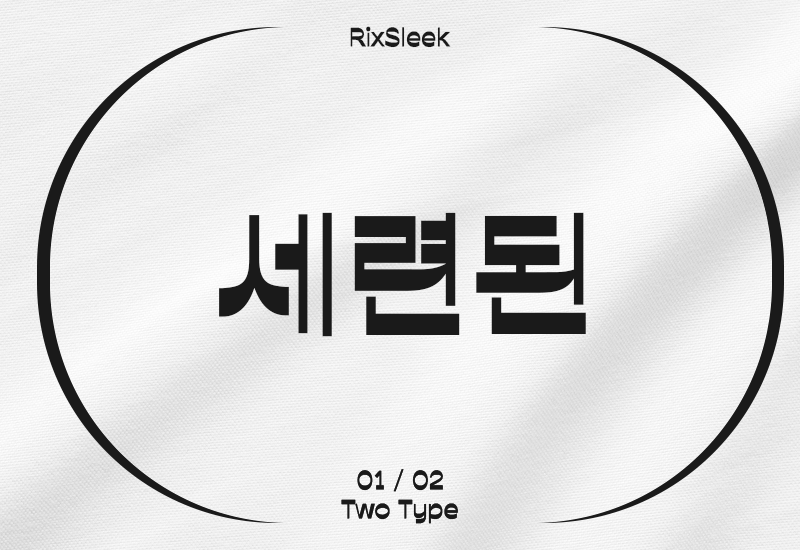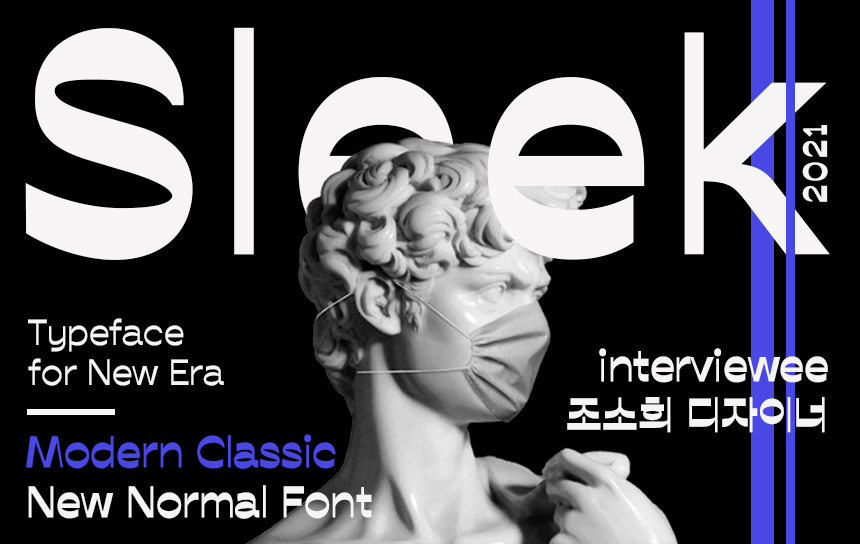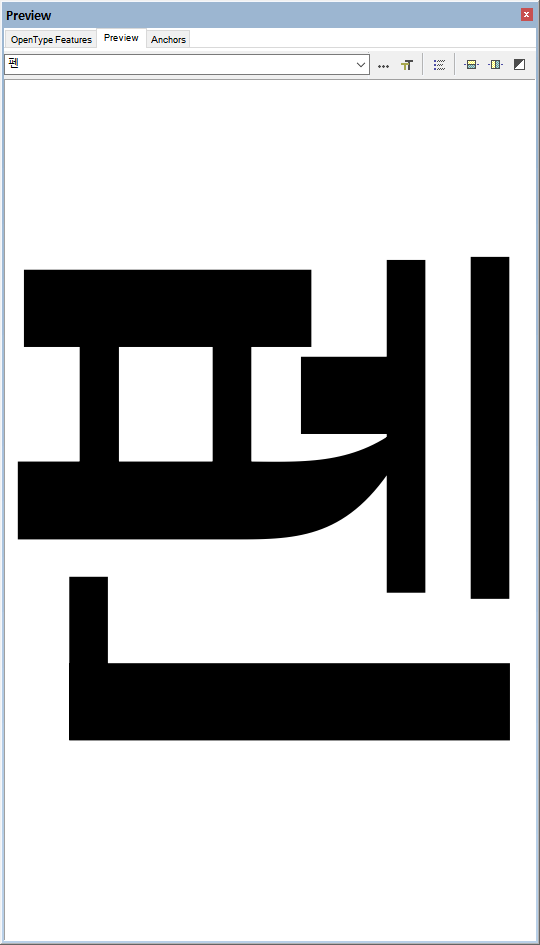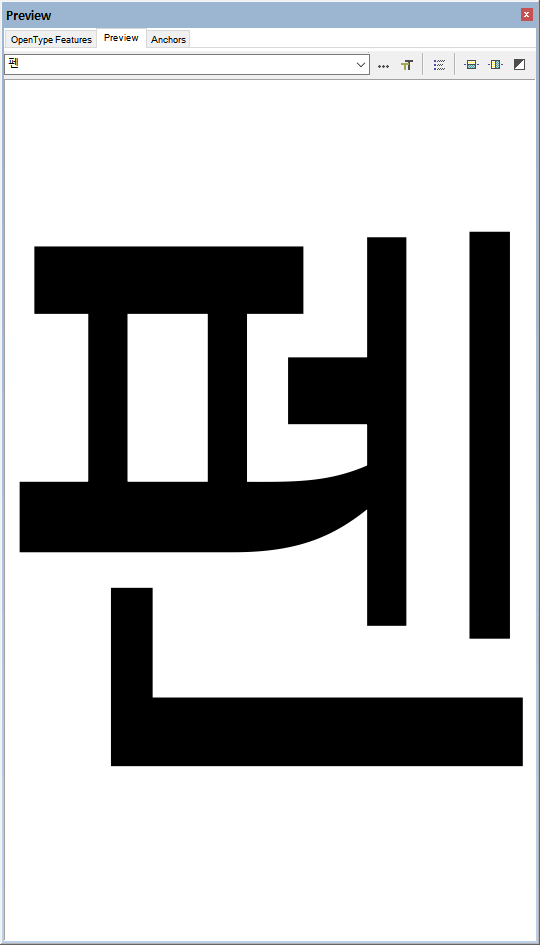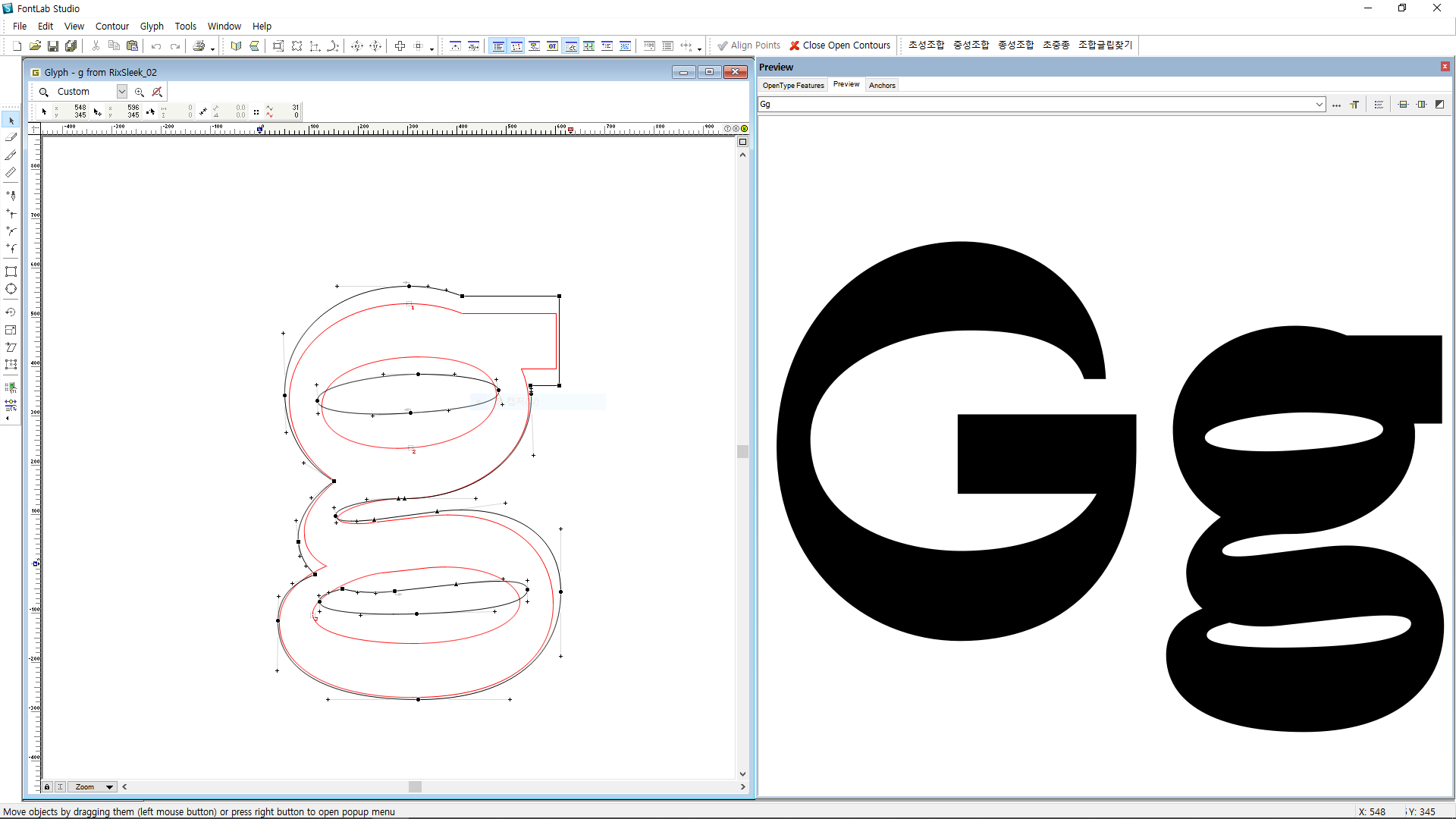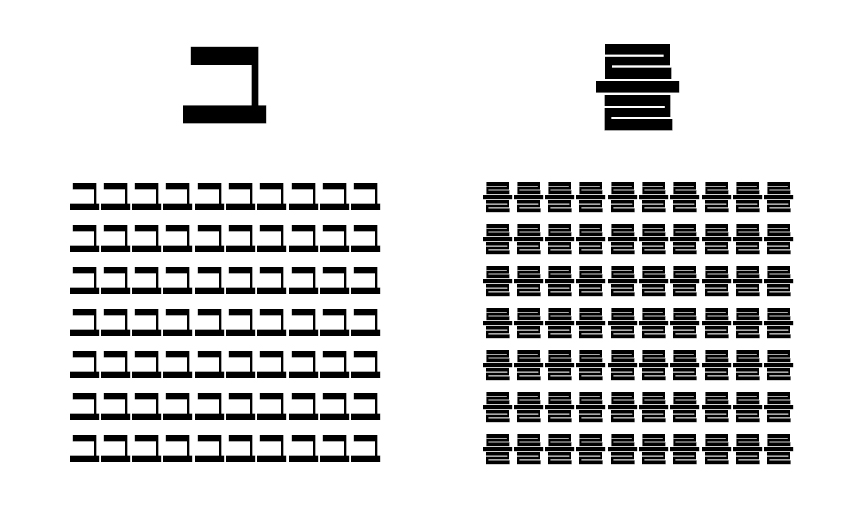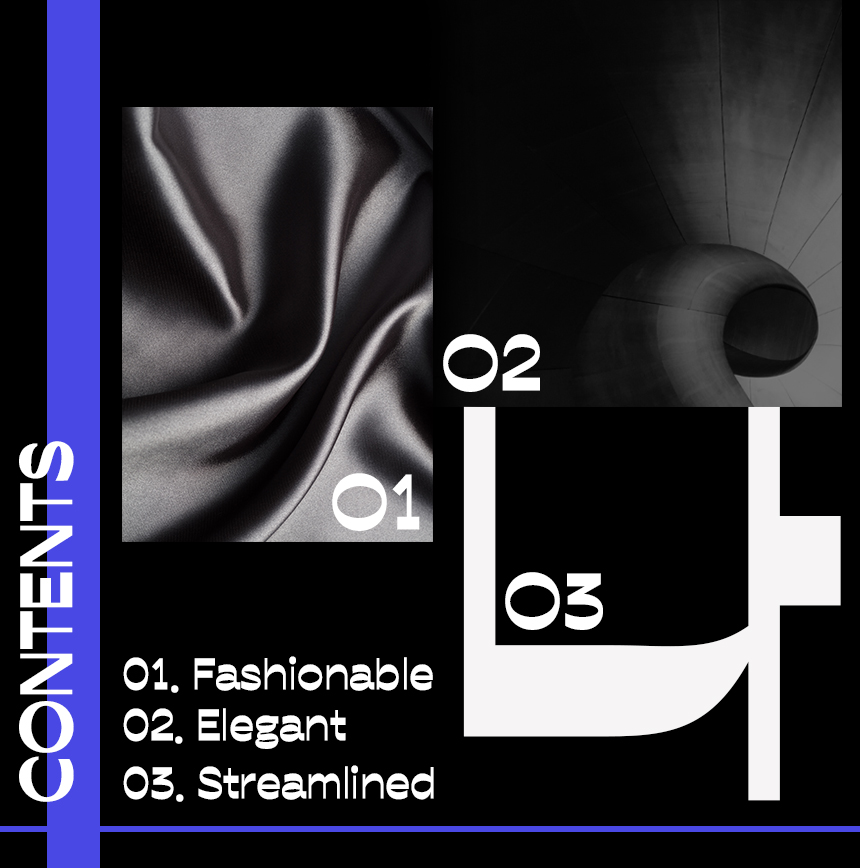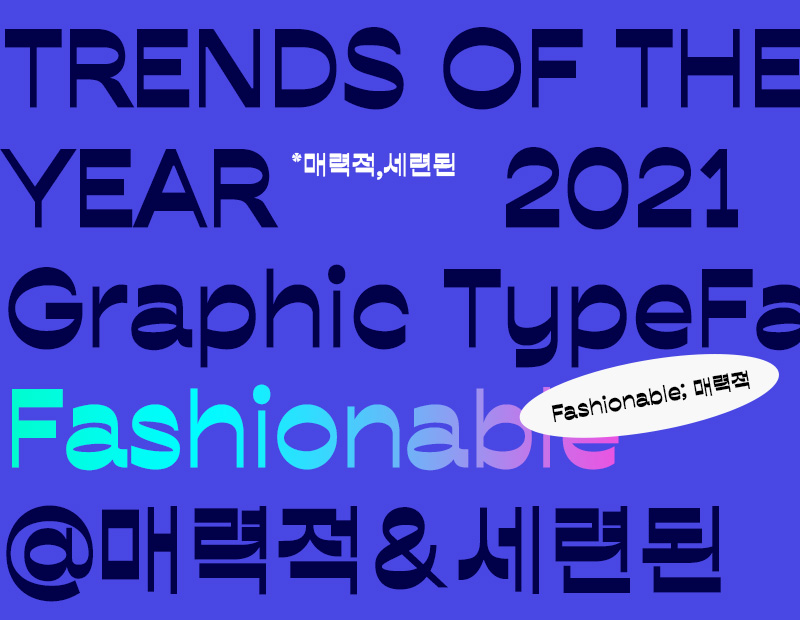
여러분 '뉴노멀(New Normal)'이라는 말을 아시나요? 시대 변화에 따라 새롭게 떠오르는 기준이나 표준을 뜻하는 용어인데요. '코로나19로 인해 마스크 패션이 뉴노멀이 되었다'와 같이 쓰이고 있는 말입니다. 이번에 소개해드릴 신서체가 바로 그런 새로운 기준이 될 폰트가 되지 않을까 싶습니다. 매끄럽게 흐르는 라인과 절제된 세련미가 묻어나는 역대급 트렌디한 폰트,「Rix슬릭」입니다. 어떤 폰트일지 기대감 가득 안고, 폰트 디자이너와의 인터뷰 먼저 들어볼게요!
이번에 작업하신 폰트는 어떻게 기획하신건지 소개 부탁드려요.
N년 전 납작 펜을 다른 각도로 써서 두께가 반전된 영문 글자를 보고 스케치를 한 게 처음 기획이었어요. 원래 더 복고형 골격이었는데, 아이디어 진행 과정에서 최정호 선생님의 공작체처럼 조금 더 편안한 골격으로 변형하면서 지금의 슬릭이 만들어졌습니다.
폰트를 보고 #세련된 #패셔너블 #모던클래식 이런 문구들이 떠올랐어요. 혹시 디자인에 영감을 받은 것이 있었나요?
아방가르드한 패션 브랜드나 메이크업 브랜드의 시즌 이미지에서 영감을 많이 받았어요. '이 멋진 이미지 위에 내 서체가 올라갔을 때 빠짐없이 어우러졌으면 좋겠다.' 하는 마음으로 제작했고, 초반에 SICKY MAG 같은 힙한 매체에서 이미지를 많이 봤습니다.
제작하면서 가장 어려웠던 부분이나 가장 공을 들인 부분이 있다면 무엇인지?
헤비한 두께의 슬릭 02의 *회색도를 맞추는 작업이 가장 어려웠습니다. 세로획이 얇다 보니 획 개수가 적은 민글자에서 다른 디자인보다 유독 회색도가 낮아 보이더라고요. 그래서 굵기 조정을 여러 번 했었어요. 영문 부분도 공을 꽤 들였는데, 이 한글 디자인에는 어떤 양식이 어울릴까 이런저런 시도를 해가면서 만들었어요. 슬릭 02에서도 그저 두께를 찌우기만 하지 않고 획이 두꺼워짐에 따라 빗겨나가듯 자리를 만들어가며 유기적인 형태로 제작했습니다.
*회색도(Grey Level)
이미지의 각 화소(pixel)의 명암이나 농도를 표현하는 수치. 회색도를 맞춘다는 것은 글자 크기의 조화나, 공간 배분, 굵기 등을 적당하게 조절해 화소값을 적정 수준으로 맞춘다는 뜻이다. 한글은 영문보다 한 글자 안에 들어가는 획의 개수가 훨씬 유동적이라서 회색도를 맞추는 작업이 더 중요한데, 예를 들어 민글자인 '그'와 받침자 '를'의 회색도를 맞추려면 '그'의 획 두께가 훨씬 두꺼워져야 한다.
'Rix슬릭'은 아무래도 보편적이지 않은 디자인적인 특징이 있는 폰트잖아요. 제작자로서 이 폰트의 가장 큰 매력 포인트를 뽑는다면?
매끄러운 시원스러움이랄까요. 스키점프대같은 곡선 자소라던가, 정원형의 ㅇ받침과 그 공간을 가르는 ㄱ이라던가 하는 부분들이 매력 포인트 같습니다.
The NEW Iconic Font RixSleek
01. 독보적인 세련미 #fashionable
「Rix슬릭」은 뉴노멀 시대에 잘 어울리는 절제된 세련미와 매력을 가진 서체입니다. 뉴노멀이란 용어는 사용된 지는 꽤 되었지만 코로나19 장기화로 인해 새롭게 정의되며 다시금 떠오르고 있습니다. 이런 시대에 발맞춰 새로운 트렌드가 될, 폰트계의 뉴-노멀 서체를 소개합니다.
글자 자체에서 트렌디함이 굉장히 돋보이도록 설계되었습니다. 명료하게 떨어지는 자소의 골격이 깔끔한 인상을 주면서 획의 두께가 일반적이지 않아 그래픽적이고 개성 있게 보입니다. 비교적 넓고 네모 반듯한 골격이 뉴트로적인 느낌도 살짝 풍깁니다.
여기서 잠깐! 폰트명 슬릭(Sleek)은 무슨 뜻인가요?
매끄럽고 윤이 나는, 매끈하고 스타일리쉬한 등의 뜻을 가진 단어입니다. 폰트의 느낌과 완전 찰떡이라 폰트명으로 선정되었답니다.
02. 우아 - 우아하게 #elegant
우아하고 클래식한 매력이 있는 서체입니다. 글을 써볼수록 느껴지는 감각적인 쉐입이 예술 쪽과의 캐미가 기대되는데요. 미술이나 패션지, 공연, 전시 등 예술 관련 콘텐츠에 아주 찰떡일 것 같은 느낌이 듭니다. 때로는 스타일리시하게, 때론 우아하게 다양한 매체에서 보여지는 모습이 벌써 상상되네요.
03. 흐르는대로 #streamlined
슬릭은 깔끔한 직선과 곡선의 조화가 돋보입니다. 실제로 글자를 쓸 때처럼 필력에 따라 점점 얇아지거나 둥글게 말려 올라가는 획들이 유기적으로 연결됩니다. Streamlined라는 단어의 뜻 그대로 유선형의 라인들이 서체에 고급스러움을 더하고 유려한 쉐입을 만듭니다.
슬릭은 총 두 가지 굵기를 제공합니다. 슬릭 01은 조금 더 보편적인 획 굵기를 가지고 있어 본문에도 편안하게 활용하기 좋게 제작되었습니다. 슬릭 02는 획 굵기의 대비를 좀 더 부각하여 눈에 띄는 헤드라인용으로 적합하며, 개성이 돋보이는 매력적인 디자인 요소들을 느낄 수 있습니다.
*소개 안하면 섭한 숫자와 영문 혼합
숫자와 영문 94자, 특수문자 986자에도 적용한 Rix슬릭의 특징. 한글과의 혼용이 조화롭도록 특히나 신경을 쓴 부분인데요. 특징이 잘 보여서 그런지 한글 폰트만큼이나 매력적이네요.
Rix슬릭 적용 이미지 샘플
고급스럽고 세련된 패키지 디자인에 활용도가 높습니다. 브랜드명이나 타이틀에는 헤드라인에 적합한 슬릭 02를 활용하고 본문에는 두께의 폭이 비교적 일정한 두께를 가진 슬릭01을 활용하면 눈길을 끄는 매력적인 디자인을 할 수 있습니다.
다채로운 공연, 예술, 페스티벌, 전시 등을 소개하는 콘텐츠에도 활용해 보세요. 개성 있는 Rix슬릭 폰트와 색깔 있는 인디 무비 페스타가 만나면? 시너지 효과를 내며 그 성격이 더욱 잘 드러나는 멋진 디자인을 보여줄 수 있습니다.
오늘은 기존과는 달라진 뉴노멀 시대에 맞는 트렌디한 그래픽 서체 Rix슬릭을 만나봤습니다. 신선함 속에서도 안정감 있게, 활용도 높은 서체를 개발하기 위해 들인 많은 고민과 노력이 돋보였던 것 같습니다. 앞으로 많은 매체에서 쓰일 Rix슬릭의 다양한 활용을 기대해 주세요!